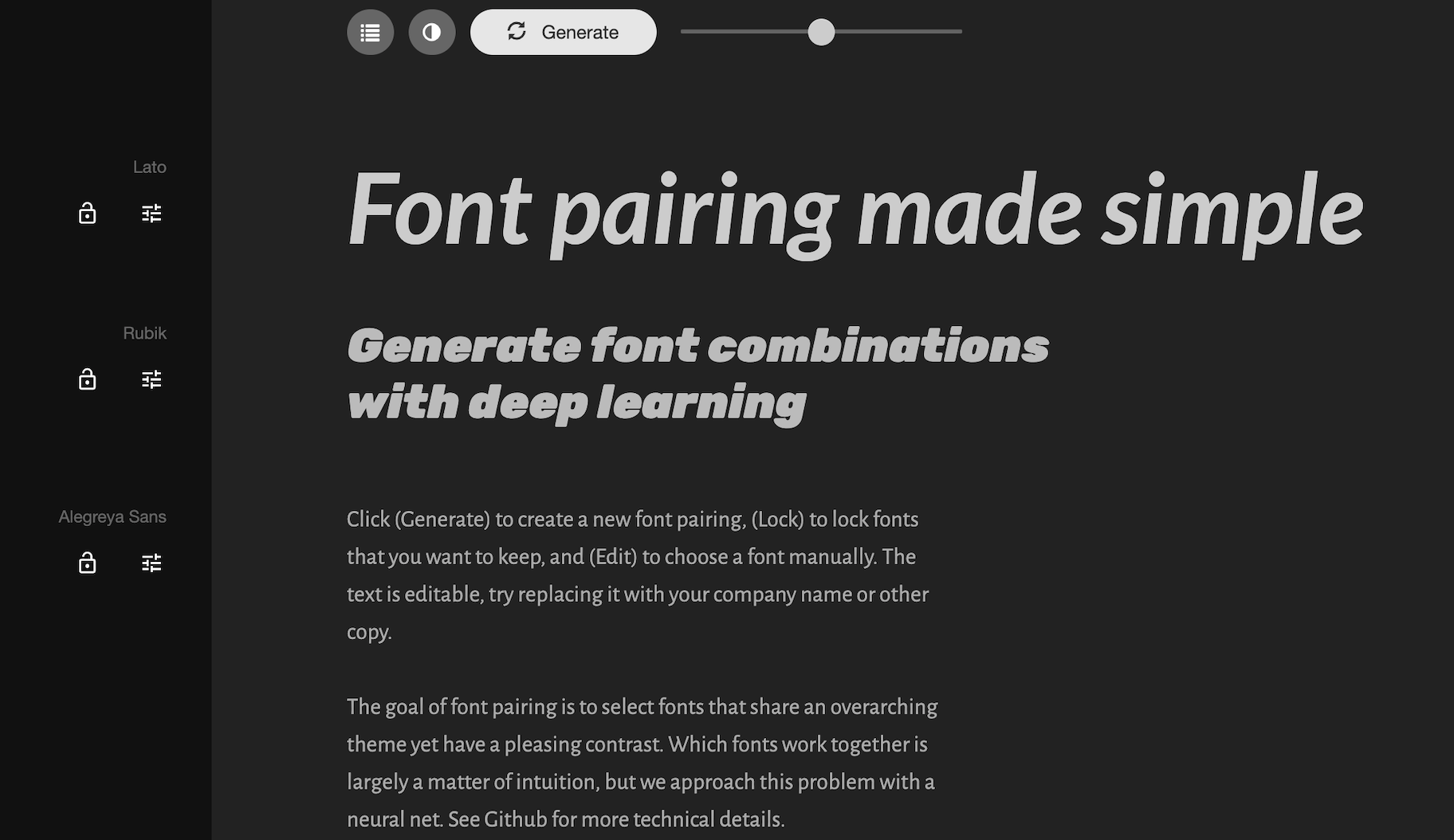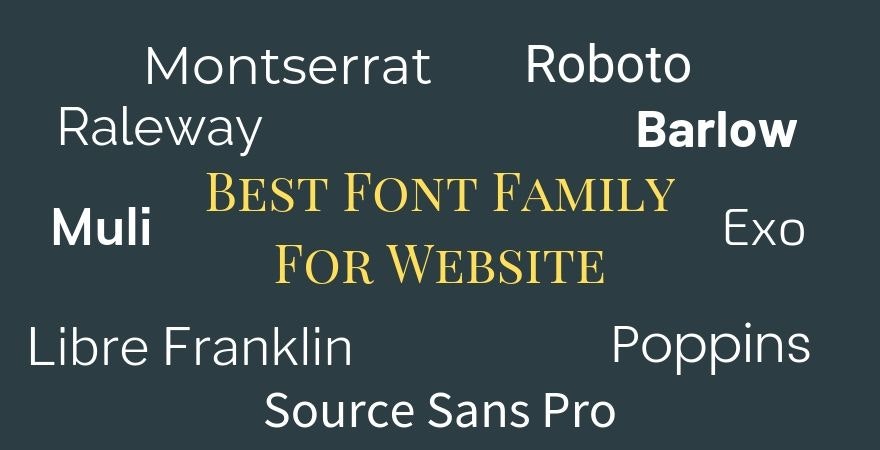
谷歌字体是你可以在网上找到的最流行的字体之一。如果你正在运行一个在线Shopify商店你就会知道你在网站上使用的是谷歌字体。谷歌web字体通常是Canva等流行品牌使用的标准字体示例。无论你是在寻找最好的谷歌字体组合,还是需要帮助寻找手写谷歌字体,这篇文章分解了你可以用于网站或设计工作的最佳网页字体。
谷歌字体是什么?
谷歌字体是谷歌创建的排版库923可免费用于商业或个人用途的授权字体。它们可以用于你的网站、设计工作、学校作业、产品等等。
如何选择谷歌字体
有几个因素可以帮助你决定选择哪种谷歌字体。在选择网页字体时,你应该考虑可读性、用途、谷歌字体组合、流行度和直观性。这里有一些想法可以帮助你更好地理解在不同的情况下应该使用哪些字体:
1.可读性
如果你正在撰写一本书、博客内容或任何文本较多的内容,你应该考虑选择衬线字体。衬线字体是一种看起来像字母有“脚”的字体。这些脚将字母连接得更紧密,这有助于它们更容易阅读。如果你看看无衬线字体,它们没有这些脚一样的扩展,这使得阅读较长的文章略显困难。
2.目的
说到选择字体,可以归结为它的用途。例如,当涉及到婚礼请柬时,您可能会使用谷歌Fonts手写字体,因为习惯上在该设置中使用草书字体。你可以选择一种更正式的字体,比如Helveticish,因为它会让你的简历看起来更简洁。如果你用的是像ABYS这样比较时髦的字体,它会在设计中突出一两个单词,而不是一些文本较多的东西。您需要选择一种适合您所使用字体的设计、上下文和行业的谷歌字体。
3.最佳谷歌字体组合
我们将在本文后面分享一些谷歌字体组合。然而,在选择一对字体时,您应该考虑它们之间的互补性。您可以将现代无衬线标题与衬线正文文本搭配使用。
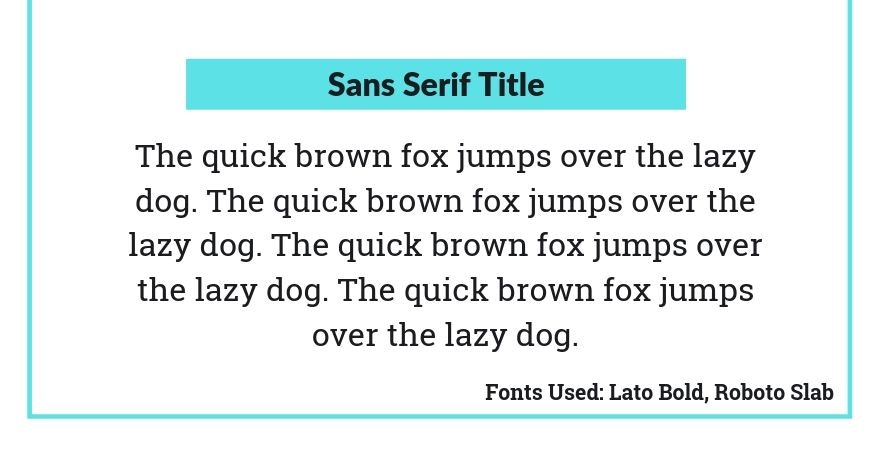
细描字体很好地用于标题,并与可读的衬线字体搭配,以创建一个干净,易于阅读的外观。
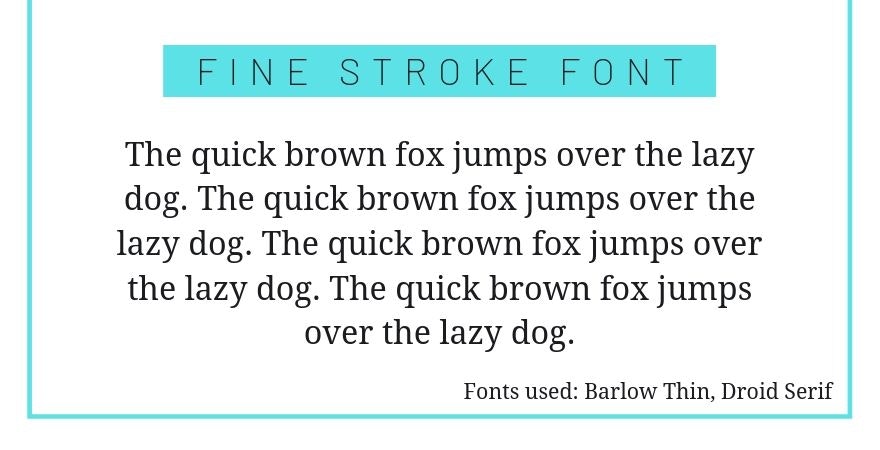
粗体衬线谷歌字体可以搭配流行的无衬线字体进行文本轻拷贝。
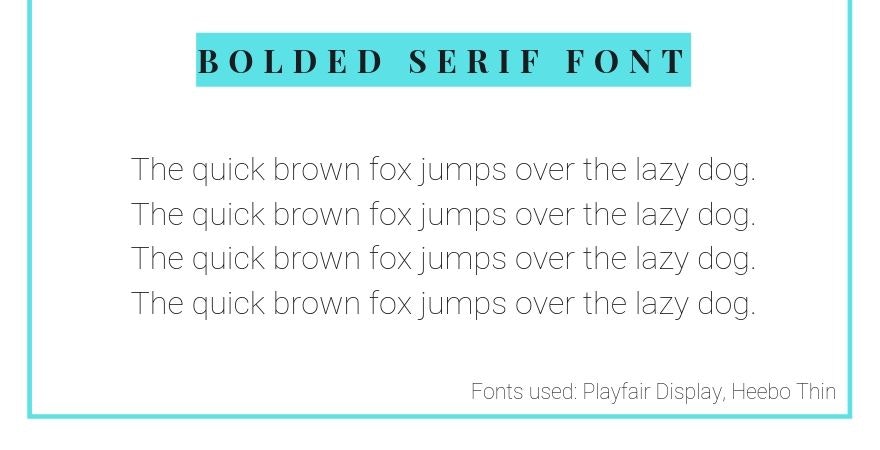
4.使用流行字体
有超过900种字体,你可能会认为它们中的任何一种都可以在任何场合使用。然而,大多数设计师通常会使用少数适用于大多数设计的字体。例如,当我在Pinterest上创建pin时,我注意到谷歌字体Playfair Display在斜体时效果很好,可以吸引点击。我在这个平台上尝试了其他几种字体,但我表现最好的引脚总是来自相同的谷歌字体。有了经验,你也会开始选择你最喜欢的几个字体。经常使用相同的谷歌字体是可以的。如果有效,不要害怕继续使用。
5.跟着你的直觉走
有时一种字体看起来是正确的,有时它看起来是错误的。虽然上面的一些规则可以帮助你确定正确的字体,但有太多的谷歌字体需要创建完美的规则。有时,你需要试验和玩弄字体选择,看看什么看起来最好。如果你理解了标准的平面设计原则和元素,你就会在整个设计中更好地了解哪种字体最有效。
为什么谷歌字体很重要
字体很重要,因为它们可以让你用字体来传达不同的色调和品牌个性。事实上,有超过900种免费的谷歌网络字体允许企业在预算有限的情况下使用不同的字体,而不需要为新字体支付许可证。
2021年将使用50+谷歌字体
最好的谷歌字体
- Roboto
- 开放无
- Lato
- 奥斯瓦尔德
- Slabo 27px
- Roboto浓缩
- 蒙特塞拉特
- Source Sans Pro
- Raleway
- PT无
谷歌字体列表
目前有923谷歌字体。下面是谷歌字体列表中的一些字体:
- 公平联盟显示
- 苦
- 自由泳中找到
- Archivo狭窄
- Alegreya无
- Ubuntu
- 深红色的文字
- Heebo
- 小屋
- 龙虾
免费谷歌字体
- 预期
- 阿布里尔Fatface
- 巴洛
- 布莉衬线
- 棒棒糖
- Ropa无
- 阿米里
- 飞碟巡航
- Zilla板
- 音乐棒极了
网站最佳字体
- 公平联盟显示
- 清唱剧一
- Roboto板
- 轴节
- 蒙特塞拉特
- 此外,
- Merriweather
- 罗拉
- 老爷
- 卡拉
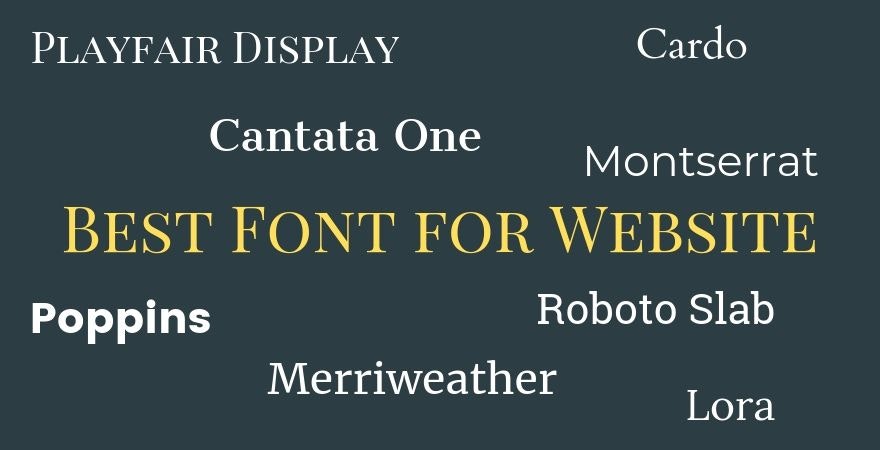
最佳衬线谷歌字体
- Roboto板
- 深红色的文字
- Slabo 27 px
- EB加拉蒙字体
- 阿米里
- Neuton
- Zilla板
- Josefin板
- 乌纳
- Abhaya自由泳
最好的无衬线谷歌字体
- Roboto
- Ubuntu
- 魔方
- 小屋
- Heebo
- 值得注意的
- 巴洛
- Archivo狭窄
- 尽快
- Ropa无
最好的谷歌字体笔迹
- 独立花
- 预期
- 从阴影到光明
- 棒棒糖
- Amatic SC
- 音乐棒极了
- 架构师的女儿
- 你无能为力
- Reenie无檐小便帽
- 苏·艾伦·弗朗西斯科
最好的谷歌字体显示
- Squada一
- Bahianiata
- Barriecito
- 圣诞之山
- 龙虾
- 阿布里尔Fatface
- 公义的
- Comfortaa
- Geostar
- 中葡一
最佳谷歌字体Monospace
- Roboto Mono
- Inconsolata
- 源代码专业版
- Cousine
- PT Mono
- 纳姆哥特编码
- 空间Mono
- 匿名职业
- Cutive Mono
- 氧气Mono
- Literata
- Lato
- 蒙特塞拉特
- 开放无
- Raleway
- 奥斯瓦尔德
- Merriweather
- 此外,
- Roboto板
- 公平联盟显示
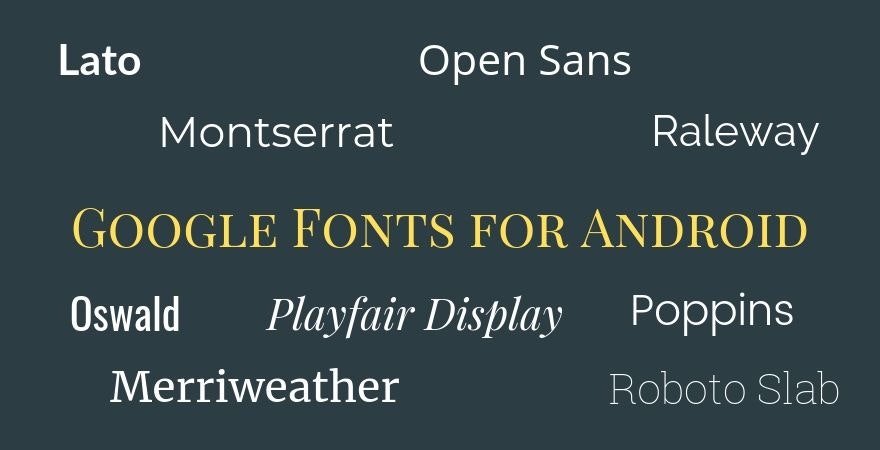
最好的谷歌字体的标志
- 卡拉
- 工作无
- 奥斯瓦尔德
- Roboto
- 魔方
- 此外,
- 小屋
- 蒙特塞拉特
- 啊
- Lato
最好的谷歌网页字体
- Cutive Mono
- 小屋
- 苦
- 下午
- 安东
- 值得注意的
- Fjalla一
- Mukta
- 万利拉轮
- 深色的怪诞
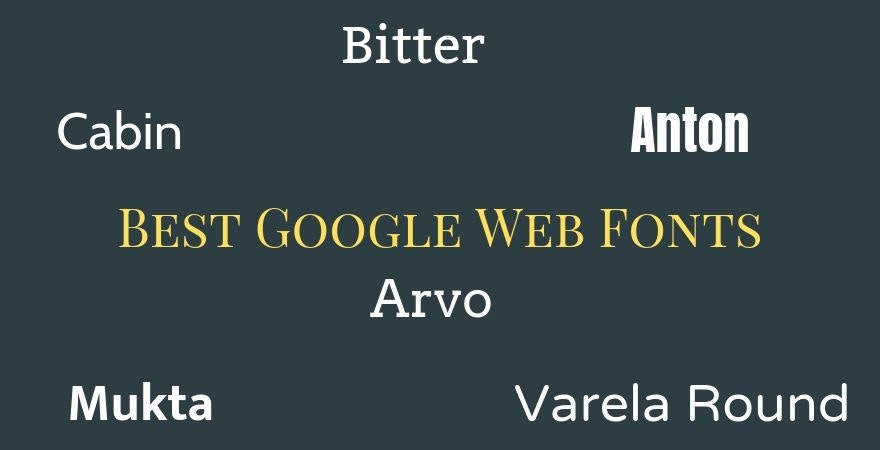
网站最佳字体系列
- 蒙特塞拉特
- Raleway
- Roboto
- 此外,
- 自由泳富兰克林
- Source Sans Pro
- 母粒
- 巴洛
- 挂式
- 天桥
谷歌字体Shopify
- 阿布里尔Fatface
- 预期
- 牧场
- Sansita一
- Inconsolata
- 匿名职业
- Fira无
- Lato
- Istok网络
- 苦
谷歌字体WordPress
- 提示
- Rokkitt
- 小胡瓜
- Alegreya
- 旧标准TT
- 轴节
- Zilla板
- 路径哥特一号
- Cantarell
- Nanum Myeongjo
最佳谷歌字体组合
- 巨大的阴影-游戏公平显示
- 蒙特塞拉特- Droid Serif
- 奥斯瓦尔德-机器人
- 拉托-梅里韦瑟
- 罗威- Roboto Mono
- Abel - Ubuntu
- Proza Libre - Open Sans
- 鲁比克-卡拉
- Bree Serif -劳拉
- Poppins -匿名专业版
谷歌字体生成器
1.帆布
帆布的字体生成器可以让你找到最好的谷歌字体组合。无论您是创建广告还是社交媒体帖子,您都可以决定使用两种字体。其中一种字体可以用作标题,另一种用作潜台词。然后,您可以使用这些字体在Canva的平台上设计和创建内容,该平台也使用各种谷歌字体。你所需要做的就是输入或选择你想要找到一个组合的字体。然后,Canva会将它的最佳匹配呈现给你。不是所有的字体都可以在这个工具上使用,但你会发现一些最好的谷歌字体。
2.字体两
字体两谷歌的谷歌字体生成器可以帮助你为网站或其他形式的内容找到字体对。全面的网站是围绕字体基于不同的字体家族。例如,您可以找到san serif和serif字体组合或显示和serif字体组合。因此,如果您正在寻找匹配两个特定的字体家族,这个谷歌字体生成器将做的技巧。
3.Fontjoy
Fontjoy微软的谷歌字体生成器显示了正在使用的三种字体。最上面的字体是标题的最佳字体,第二种字体和副标题,第三种字体是正文。你不需要全部使用这三种字体。例如,如果你正在为你的网站寻找标题和正文字体,你可以只选择第一和第三种字体。这个工具的伟大之处在于,您可以看到字体的作用,以帮助您了解这种字体组合是否适合您的需求。
4.分析
分析可能不是一个谷歌字体生成器在传统意义上。然而,它教育你什么是最流行的谷歌字体。如果你想坚持最流行的网页字体,你很快就会知道Roboto是在列表的顶部。在心理学上,有一种现象叫做“暴露效应”,意思是人们喜欢自己最熟悉的东西。通过坚持使用最好的谷歌网页字体,人们“理论上”会更喜欢他们看到的字体。
结论
谷歌字体可以用于社交媒体图形,t恤设计,网站,和其他营销元素为您的在线业务。在选择字体时,记住要考虑字体的色调、可读性和适当性。如果你发现自己在工作中使用相同风格的字体也没关系,设计师总是这样做。专注于选择最适合你的目标的谷歌网页字体,它将帮助你完成设计的外观。